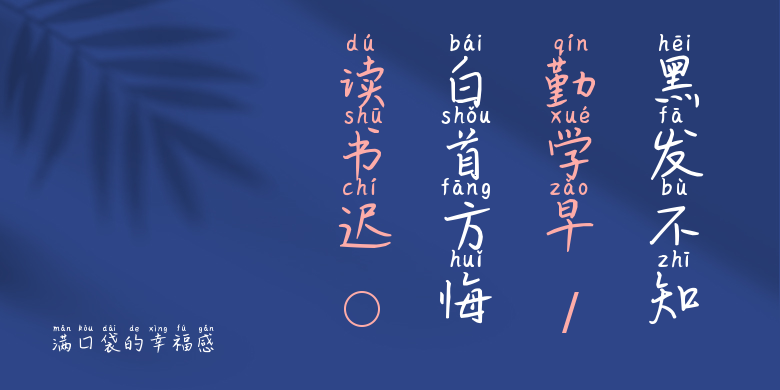
满口袋的幸福感
满口袋的幸福感,这款字体结构工整、笔画清晰,兼顾美观与易读性,适用于标题、正文、海报、包装、LOGO 等多种场景。字形优雅稳定,风格百搭耐看,适配日常排版与创意设计,让文字呈现更舒适、更具质感。满口袋的幸福感一笔一画,皆是细节,以均衡的比例、流畅的线条打造舒适视觉体验,字形端正大气,风格简约现代。无论是商业设计、品牌宣传还是日常排版,都能轻松驾驭,让文字更有格调与力量。满口袋的幸福感字体下载。